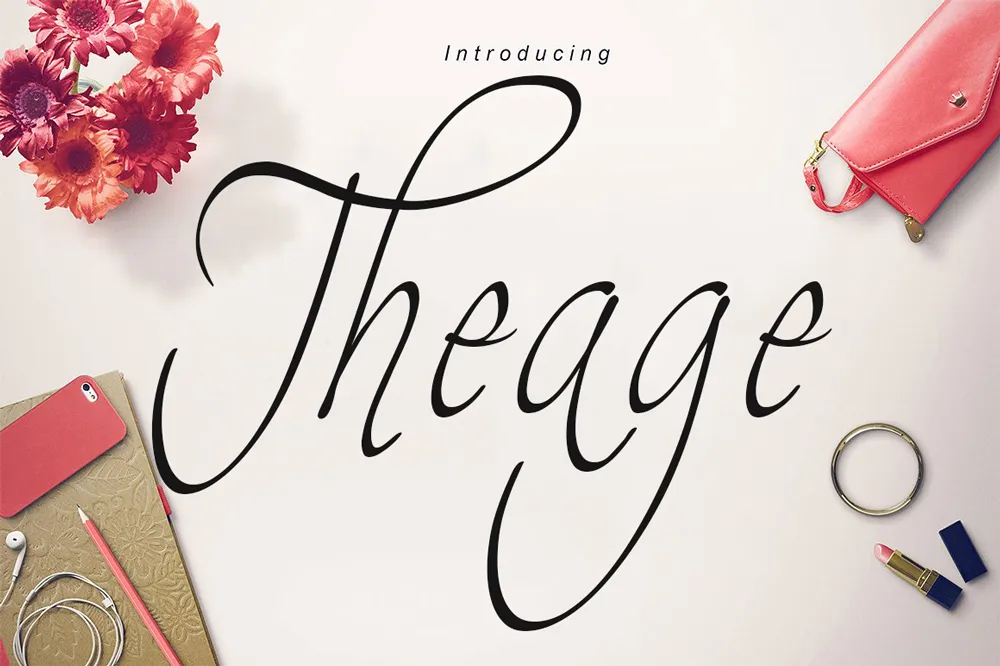
Theage Script Font – Download Grátis
Introduzimos Theage script font! Uma nova forma de escrita a mão. Ela é completamente manual, com uma sensação excepcional. Você encontrará algo quase familiar ao olhar por ela, pois está muito próxima à sua própria escrita a mão. Através do design cuidadosamente elaborado pelo Designer Typeface, você pode experimentar o verdadeiro sentimento da escrita a mão sem precisar escrever com um pincel. O Theage script font oferece uma experiência de digitação única e autêntica, ideal para aqueles que buscam um estilo peculiar na sua produção visual. Seja em um website ou aplicativo, o Theage Script Font certamente tornará seu design mais destacável e pessoal, ao mesmo tempo que mantém a essência da sua personalidade. Não hesite em baixá-lo hoje!